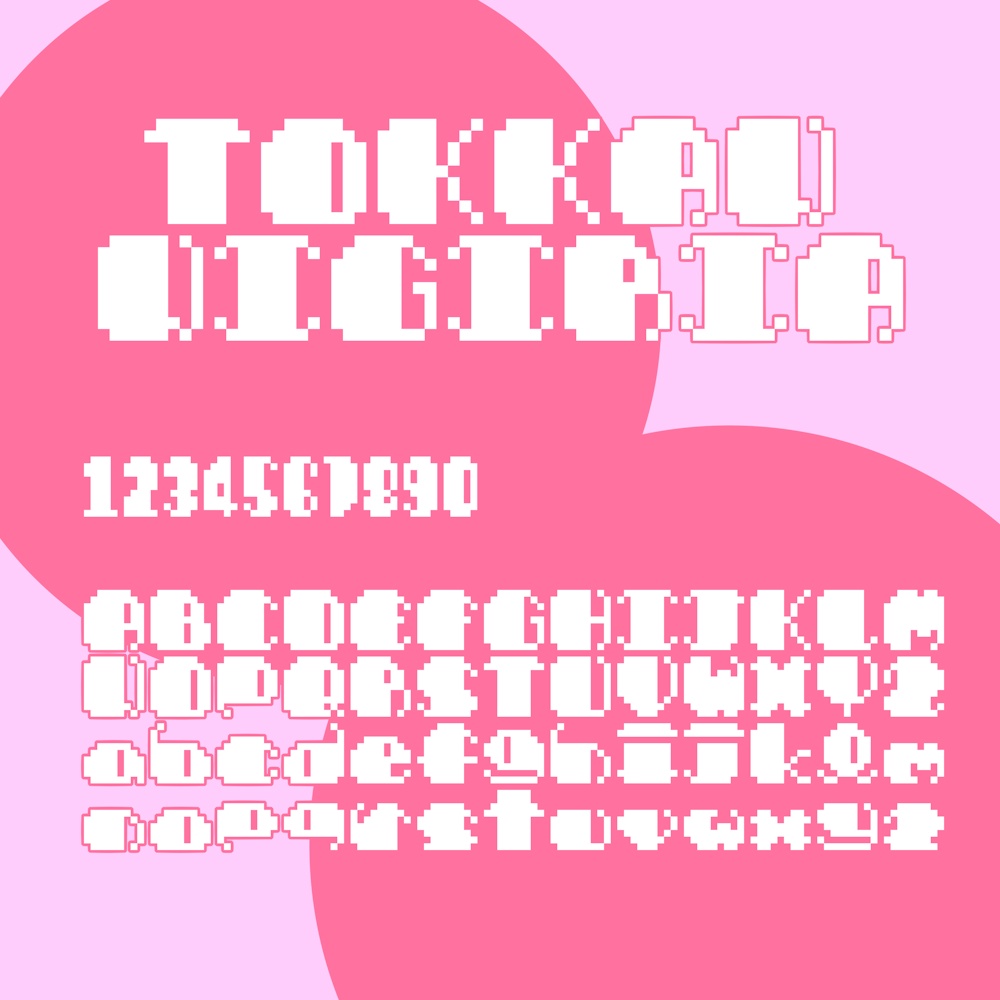
多忙のため事前に開けておきます。(〜R8.4.10まで配布予定) ______________________________ 毎年4/10&気が向いたとき&イベント時に配布予定のフォントです。 ______________________________ 「トッカンニギリア(Qma-tokkannigiria.ttf)」は フォント作成について何も知らない触手(加熱九真/shokushuQ)が https://www.pentacom.jp/pentacom/bitfontmaker2/ さんの力によって、手打ちしてつくったドットのフォントです。 何も知らないので横書きのことしか考えていません。 なお、トッカンニギリアはトッカンニギリ( https://nekkiq.booth.pm/items/6799439 )をベースにしています。 ■利用範囲 個人利用、商用利用、ウェブフォントやゲームなど独自性のあるコンテンツへの組み込みは自由です。 年齢制限が必要なコンテンツにもご使用頂けます。 ■禁止事項 犯罪行為や違法行為への使用、改変前のフォントファイルを単独で再配布することは禁止します。 商標登録など、第三者が本フォントを使用できなくなる行為は禁止します。 ■改変と再配布 収録文字の8割以上を改変し、本規約を改変前フォントの規約として明記・同梱することで再配布可能です。 ■免責 本フォントの使用により生じた損害について、制作者(加熱九真/shokushuQ)は一切の責任を負いません。 ■その他 必須ではありませんが、使用の際にクレジット記載があると嬉しいです。 ■収録文字について 全角・半角ともに同じデザインです。 全角と半角のピクセル数が2:1ではありません。 全角スペースはかなり中途半端な幅です(修正方法模索中) 半角スペースを1ピクセル分にしてあるので、それでうまく調整してください。 ■全角 1234567890 ABCDEFGHIJKLMNOPQRSTUVWXYZ abcdefghijklmnopqrstuvwxyz ■半角 0123456789 ABCDEFGHIJKLMNOPQRSTUVWXYZ abcdefghijklmnopqrstuvwxyz